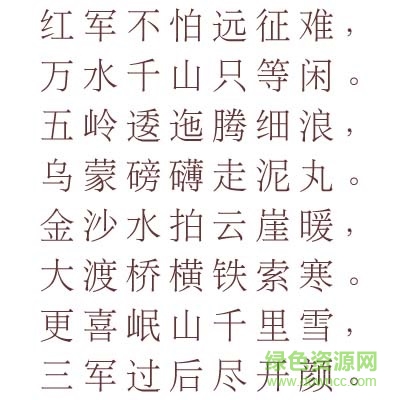
長(zhǎng)城報(bào)宋體是根據(jù)宋體改編而來的一款簡(jiǎn)體字體。該字體雖然也是橫細(xì)豎粗,但是,并不是很明顯,更具自己的特色。趕快來綠色資源網(wǎng)下載體驗(yàn)吧!
1.中國(guó)的字體設(shè)計(jì)是在印刷術(shù)的產(chǎn)生和發(fā)展中應(yīng)運(yùn)而生的。在古代,中國(guó)的字體設(shè)計(jì)曾有過輝煌的歷史時(shí)期,在宋朝時(shí)進(jìn)入黃金時(shí)代。
2.清朝末年,鉛字排版印刷術(shù)傳入中國(guó),字體設(shè)計(jì)進(jìn)入鉛字時(shí)代。這個(gè)時(shí)期的字體設(shè)計(jì)既要帶有傳統(tǒng)文化的審美慣性,又要符合鉛字印刷的工藝要求,字體設(shè)計(jì)走到了轉(zhuǎn)折的關(guān)口。
3.鉛字印刷是印刷走入機(jī)械化、工業(yè)化時(shí)代的標(biāo)志,但在這一時(shí)代里,印刷字體設(shè)計(jì)卻始終無法超越手工勞動(dòng)的制約,無法擺脫刻模、鑄字、撿字、排版等一系列印前繁雜工藝的束縛